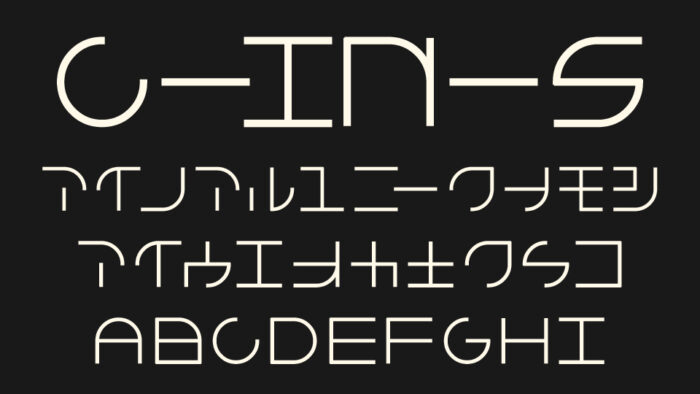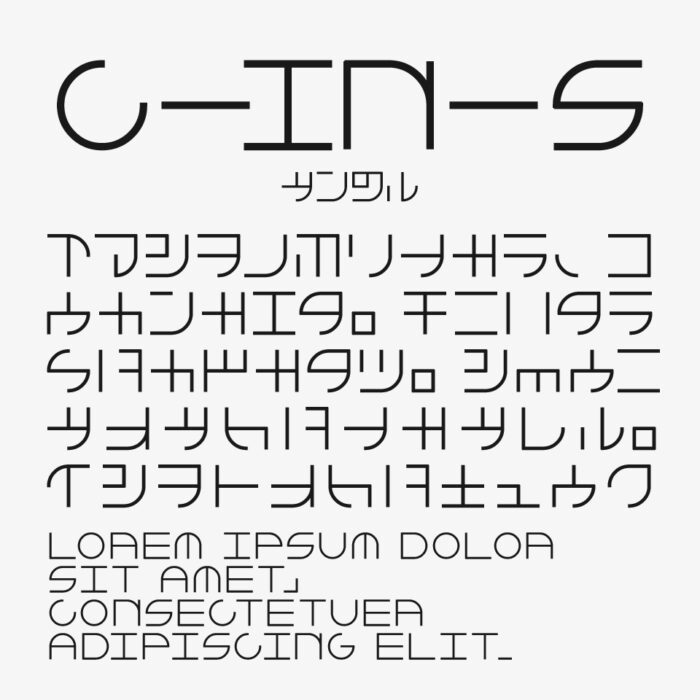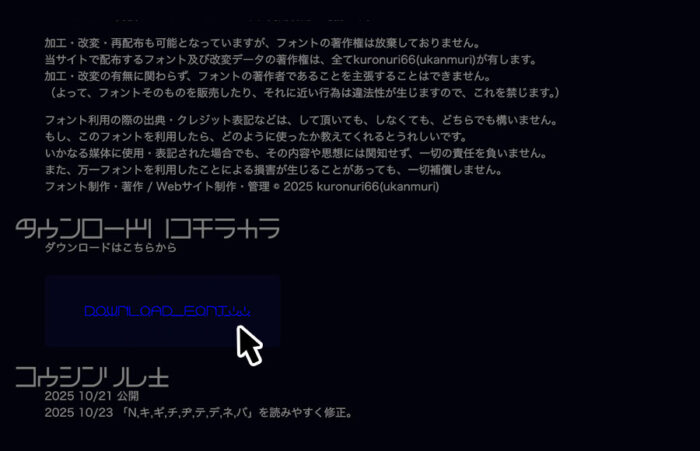
c-in-s(シー イン ス)
c-in-s(シー イン ス)フォントは、「四角のなかの円の中の十字」をテーマに制作されたデザインフォントです。
英数字だけでなく、ひらがな・カタカナまでもが一貫したルールで制作されており、ミニマルで幾何学的なデザインです。まるで暗号のような不思議なビジュアルで、SF映画や未来都市のUIに出てきそうな雰囲気をもち、デジタル感を演出したい場面にぴったりなユニークなフォントです。
収録文字は、ひらがな・カタカナ・アルファベット・数字・記号が収録されています。